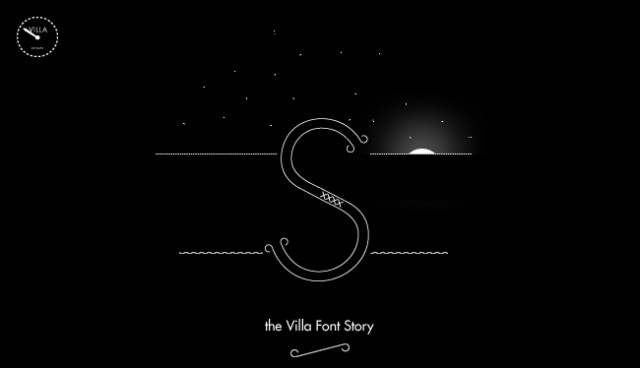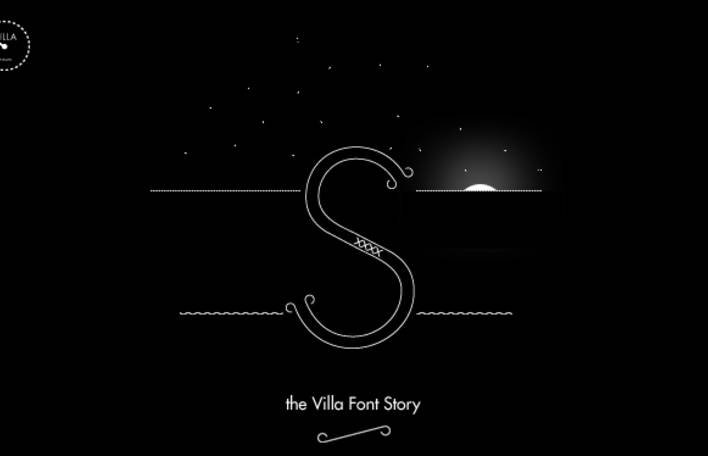
C’est l’histoire d’une Font, la « VILLA FONT ». J’ai créé cette Font après un voyage à DINARD.
« VILLA FONT » s’inspire des maisons classées (XIX et XX siècle) de cette ville bretonne de bord de mer.
Dans ce film d’animation, chaque lettre est à l’image d’une villa.